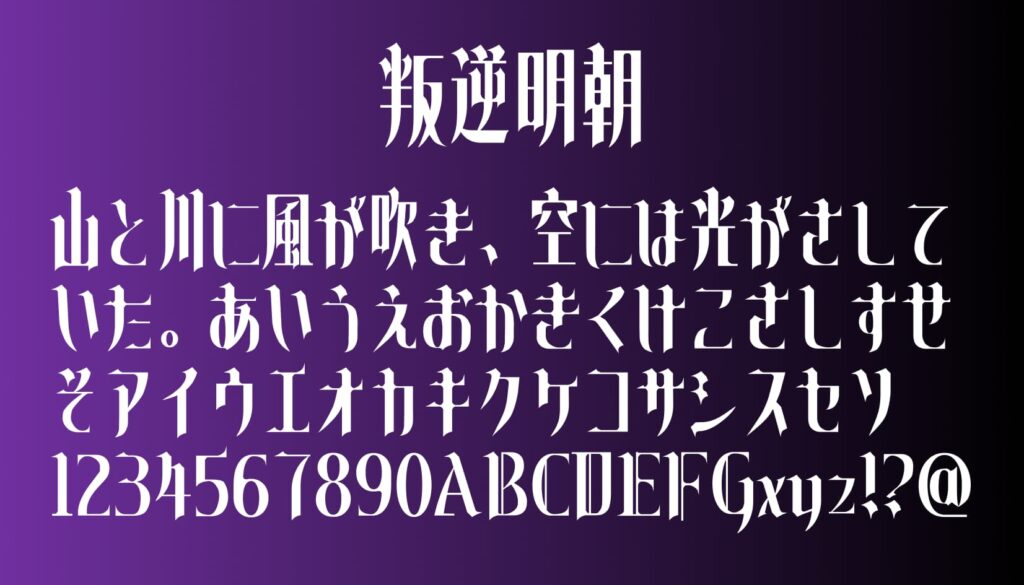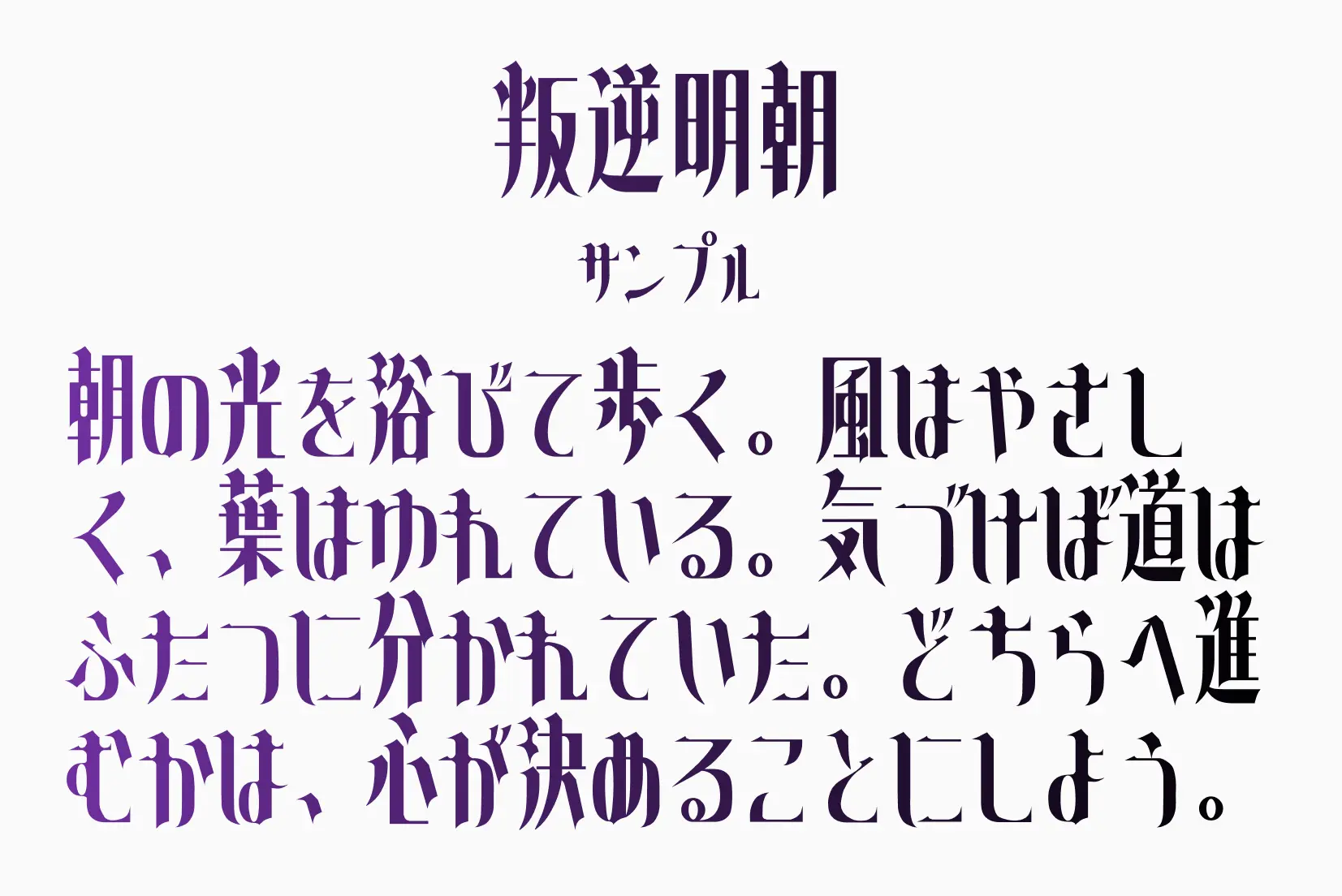
アニメ『まどかマギカ』のロゴをベースにした装飾系フォントで、鋭いハネやトゲ感のあるシルエットが特徴。中世ファンタジーやゴシック調の雰囲気を強く演出でき、タイトルやロゴに使うだけで一気に“物語感”が出るのが魅力。可読性よりも世界観重視のデザイン向きで、MVやバナー、ゲーム系ビジュアルとの相性が抜群。日本語フォントでは珍しいブラックレター風の表現ができる、かなり個性派な一本。
叛逆明朝